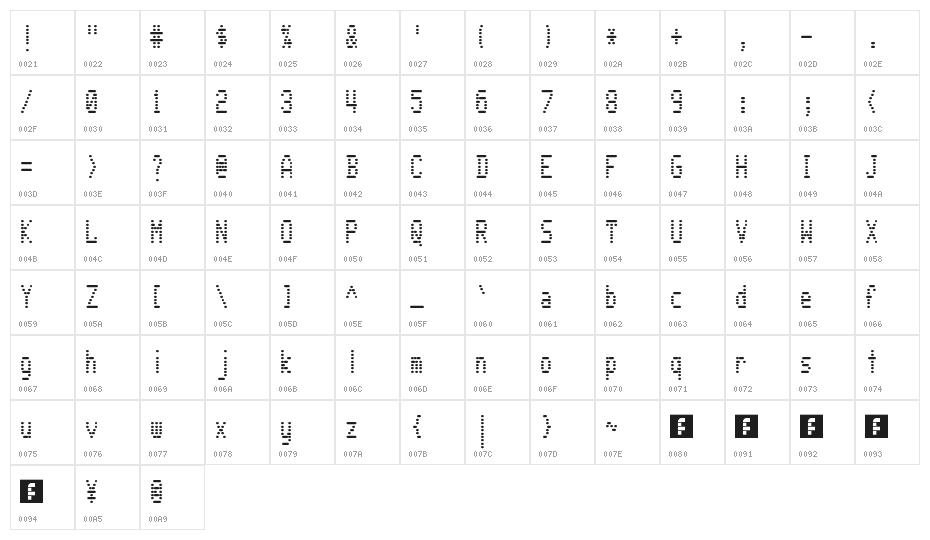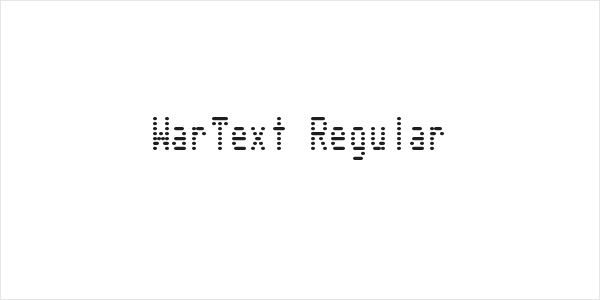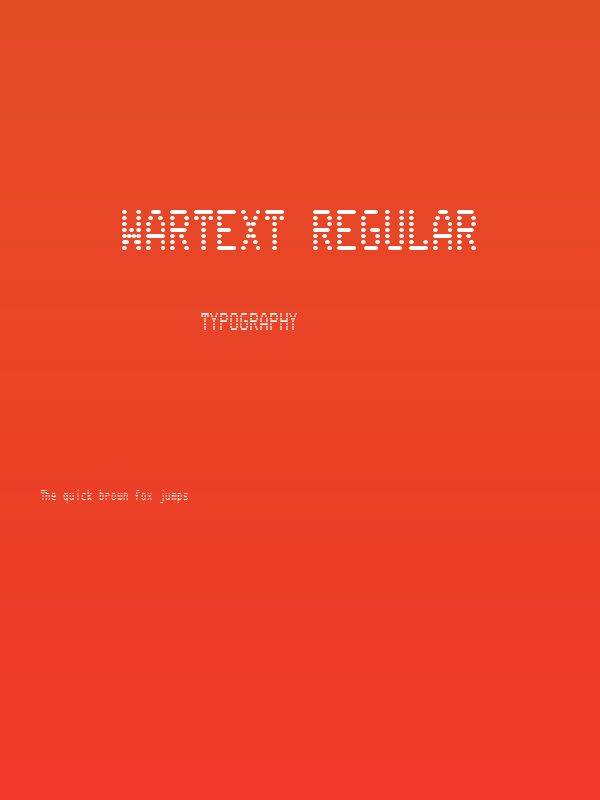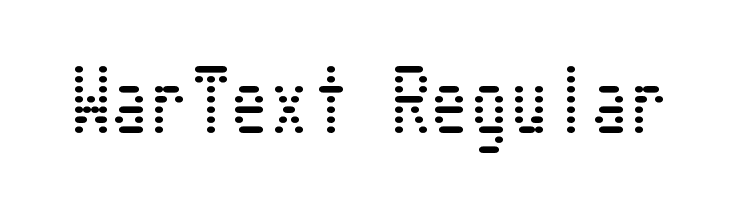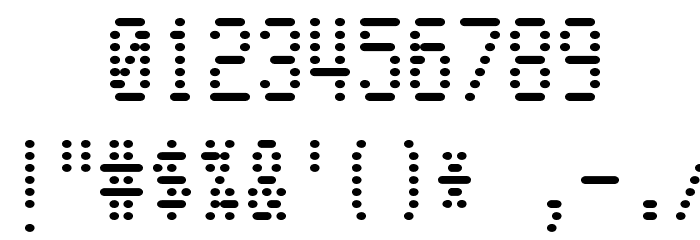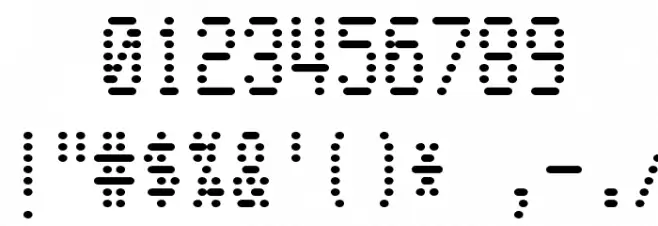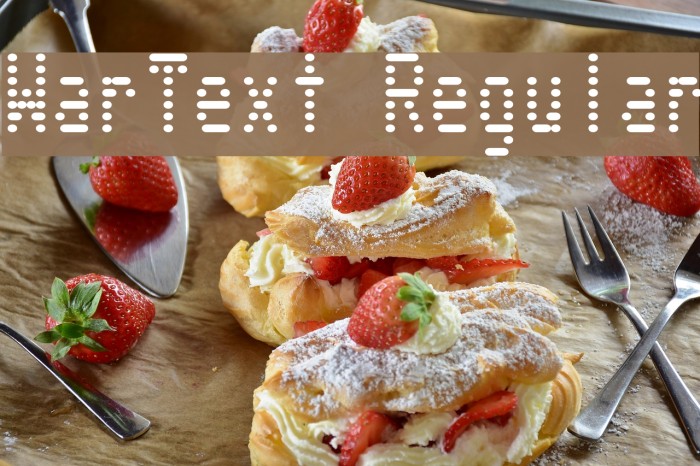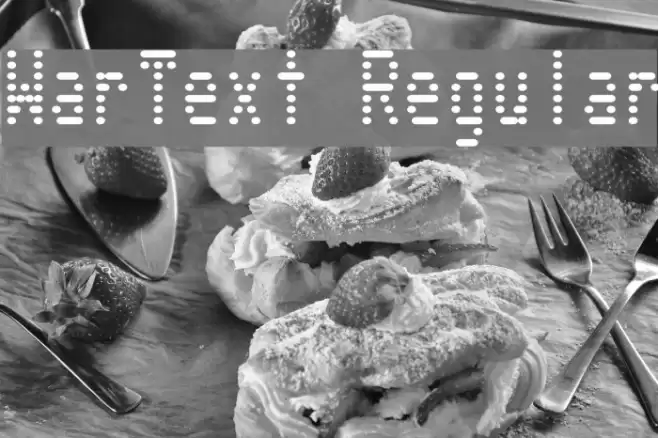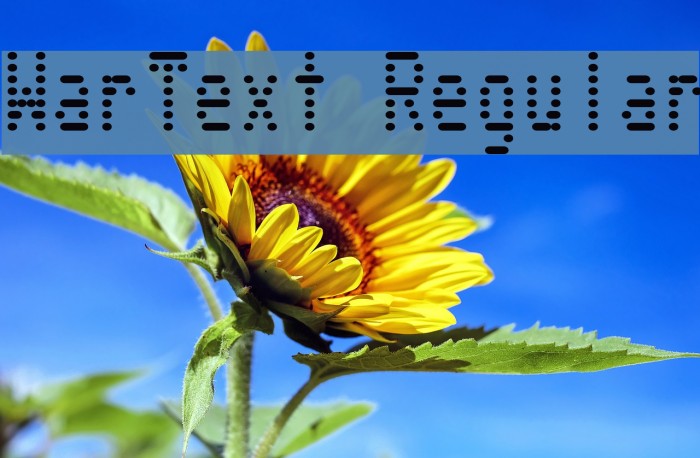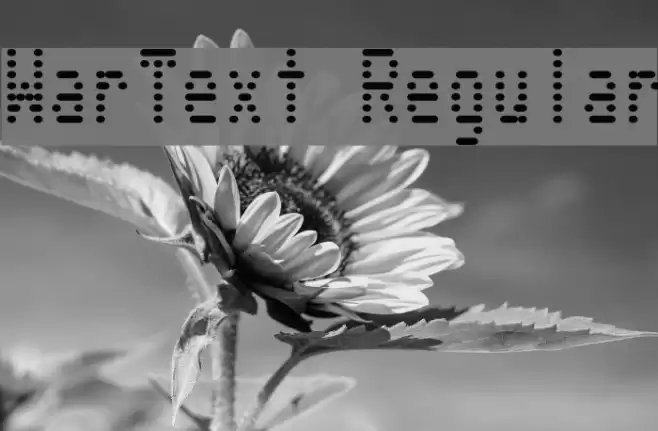
WarText Regular Font
| Caz de utilizare | Headlines, Logos, Digital displays |
| Proiecte propuse | Ideal for tech-themed designs, digital art, futuristic branding, or any project seeking a modern and innovative look. |